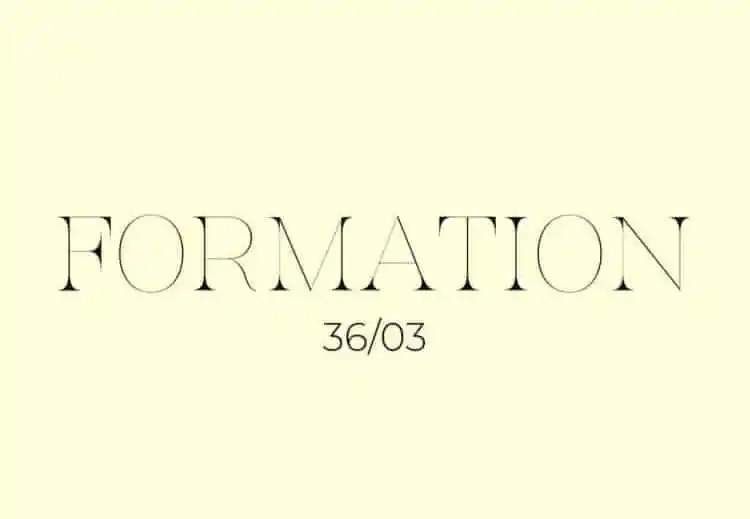
A fonte ‘Formation Serif’ é uma paixão para quem valoriza a elegância clássica na design gráfico. Com seu estilo serífero, ela captura imediatamente a atenção e evoca emoções antes mesmo de você ler o texto. Esta font foi criada pelo designer Justin Penner em 99designs, um ambiente propício para novos projetos de criação visual. A ‘Formation Serif’ se ajusta perfeitamente aos mais sofisticados ambientes de design, como logos e títulos de revistas ou jornais. Também é ideal para qualquer projeto que busque transmitir elegância e classe. Seja para criações digitais com uma atmosfera única ou para elementos físicos que precisam ser leves e atemporais, essa font oferece a perfeição em termos de estilo. Composto para se adaptar às mais diversas necessidades do design, é um dos recursos indispensáveis para quem busca projetos que combinem sofisticação com autenticidade. Seja você designer gráfico ou profissional que trabalha com elementos visuais, ‘Formation Serif’ é uma fonte que reflete seu gosto e capacidade criativa.